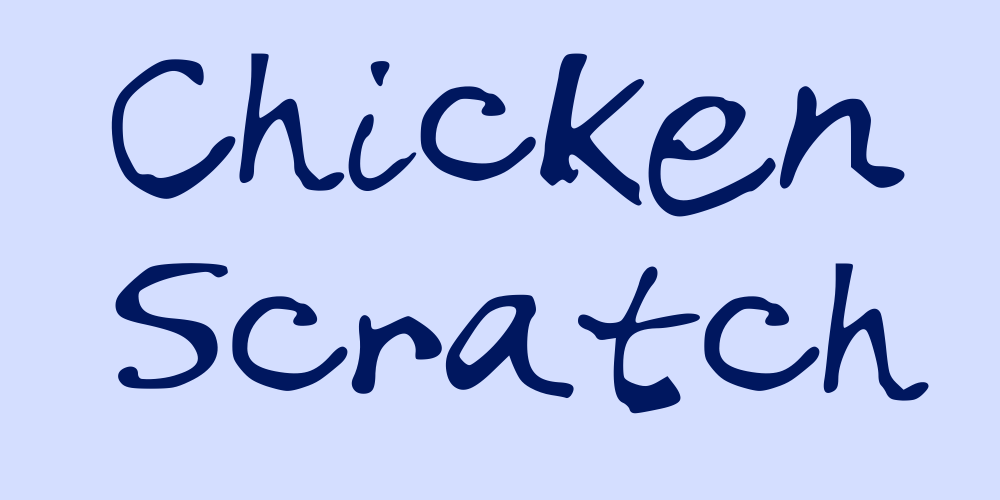
Aqui está uma descrição envolvente para a página de download da font ‘Chicken Scratch’, desenvolvida pelo designer Hamilton: Atravessamos as calçadas urbanas e mergulhamos nas folhas de papel, deixando que nossas mãos fiquem suaves com tinta ou digitalizadas em tela. Essa fonte é uma cópia autêntica das minhas digitais, do estilo informal da escrita à mão livre que desenhou durante anos. Hamilton, designer meticuloso e apaixonado por letras, criou ‘Chicken Scratch’ para oferecer um toque diferente, um pouco de personalidade na sua composição visual. Não é uma fonte formal ou sofisticada, mas uma abordagem informal que chama a atenção por meio do seu grafiato livre, da forma como as letras se juntam e desviam em cada linha. Inspirado nas maneiras como as crianças adoram escrever em seus cadernos de notas, sem pressa ou preocupação, ‘Chicken Scratch’ é perfeito para quem busca uma fonte que traga um pouco da naturalidade e do entusiasmo das letras à sua arte. Ele é ideal para aqueles que buscam um estilo casual e descontraído na criação visual – seja em design gráfico, ilustrações ou qualquer projeto onde a escrita ao vivo toma o centro. Seja você designer de moda, arquiteto, artista digital, ou até mesmo um fotógrafo amador procurando por uma maneira única de personalizar seu trabalho final com um toque autêntico e não formal – ‘Chicken Scratch’ pode ser a fonte perfeita para você.